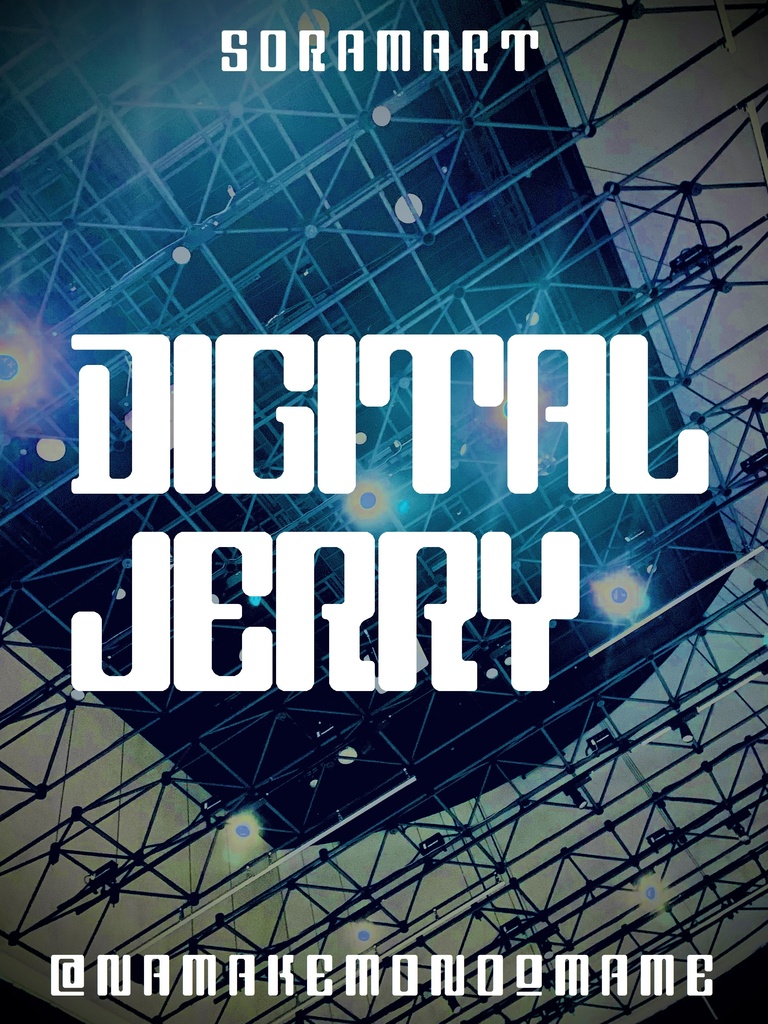
そらマートフォントデータ”Digital Jerry”Digital2,500 JPYAdd to CartBuy a GiftAbout Giftサイバー感と柔らかな印象の両立を目指した"Digital Jerry"です。 「TrueTypeフォントファイル」という形式です。 ダウンロードした後、Zipファイル内のデータをインストールしてお使いください。 このフォントは商用利用可となっております。 お客様の制作・創作活動のお役に立てれば幸いです。 ※使用上の注意事項などは、添付のReadmeをお読みください。そらマートVisit FANBOX!Fontsフォントデータ”Tetra Pixel Dash”そらマート2,500 JPYFontsフォントデータ”Tetra Pixel Fluid”そらマート0 JPYFontsフォントデータ”Tetra Pixel”そらマート0 JPYFontsフォントデータ”Neon-Lit Empire Long”そらマート2,500 JPYFontsフォントデータ”Neon-Lit Empire”そらマート2,500 JPYFontsフォントデータ”Jumping Meteor Drop”そらマート2,500 JPYFontsフォントデータ”Jumping Meteor Wide”そらマート2,500 JPYFontsフォントデータ”Jumping Meteor”そらマート2,500 JPYFontsフォントデータ”Ragtime Key Tall”そらマート2,500 JPYFontsフォントデータ”Ragtime Key Bold”そらマート2,500 JPYFontsフォントデータ”Ragtime Key”そらマート2,500 JPYFontsフォントデータ”Cocoon Bullet Emerge”そらマート2,500 JPYFontsフォントデータ”Cocoon Bullet Slug”そらマート2,500 JPYFontsフォントデータ”Cocoon Bullet”そらマート2,500 JPYFontsフォントデータ”Frost Quartz Wide”そらマート2,500 JPYFontsフォントデータ”Frost Quartz LL”そらマート2,500 JPYFontsフォントデータ”Frost Quartz”そらマート2,500 JPYFontsフォントデータ”Highway Surfer Loud”そらマート2,500 JPYFontsフォントデータ”Highway Surfer Long Leg”そらマート2,500 JPYFontsフォントデータ”Highway Surfer”そらマート2,500 JPYSee More